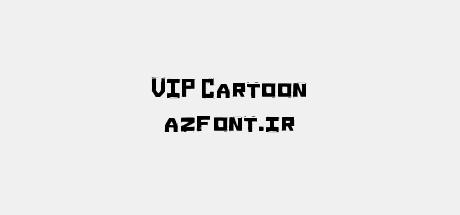
VIP Cartoon
فونت زیبای رایگان VIP Cartoon
قلم زیبای VIP Cartoon از سری قلم های بسیار زیبا برای تایپوگرافی و لوگو تایپ می باشد.این قلم در وزن Regular و توسط (Ghanem-ar.photoshop.3abber.com). 2014. All Rights Reserved طراحی و منتشر شده است.